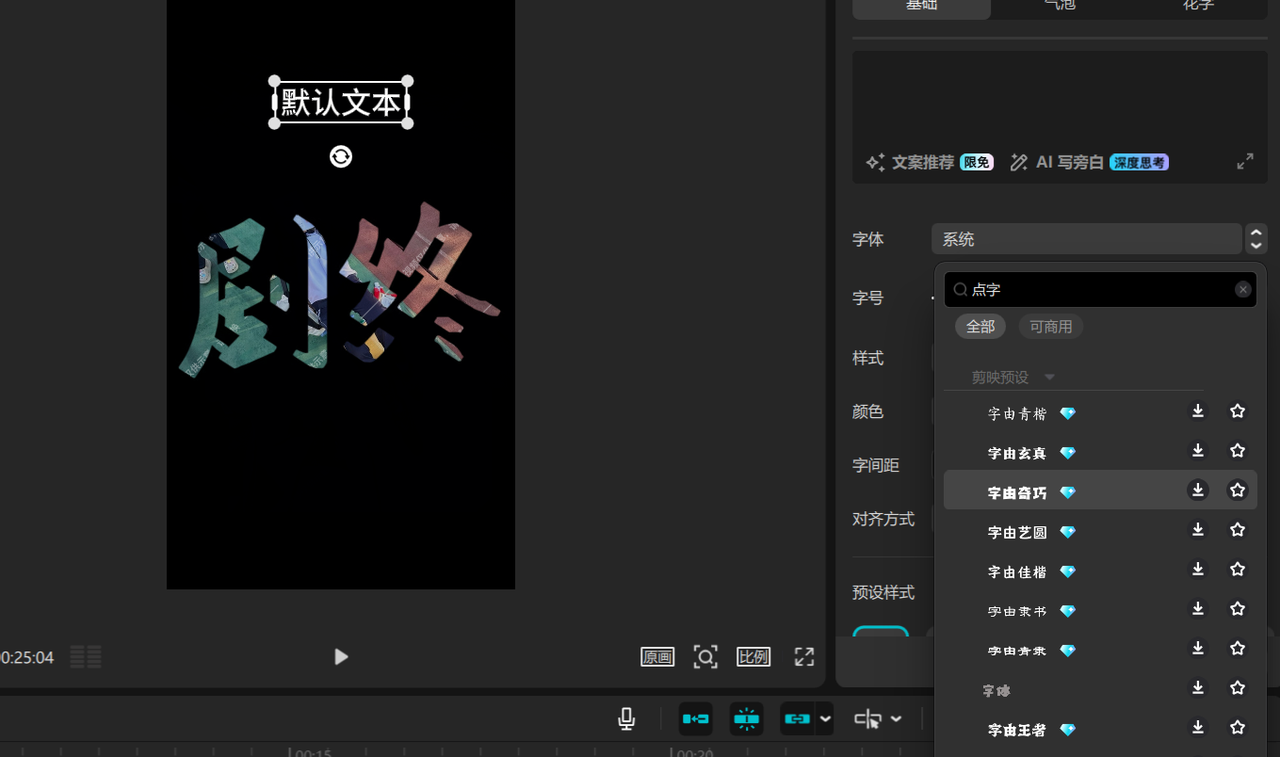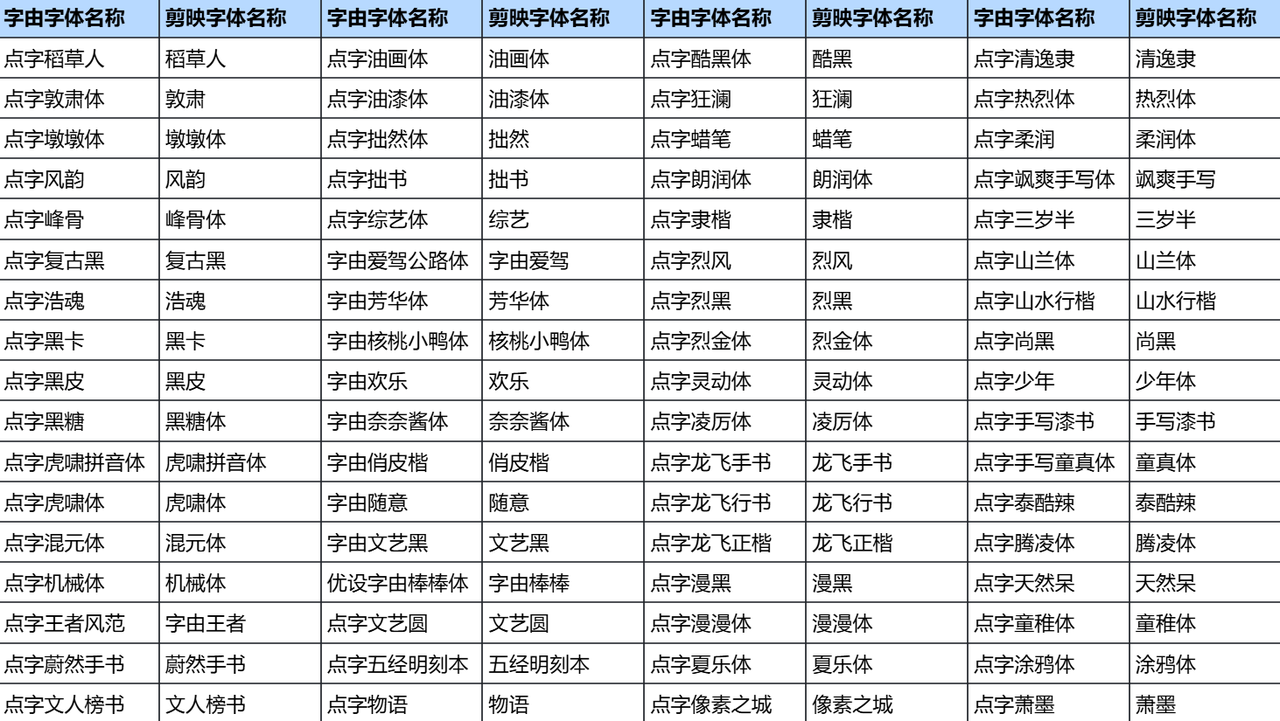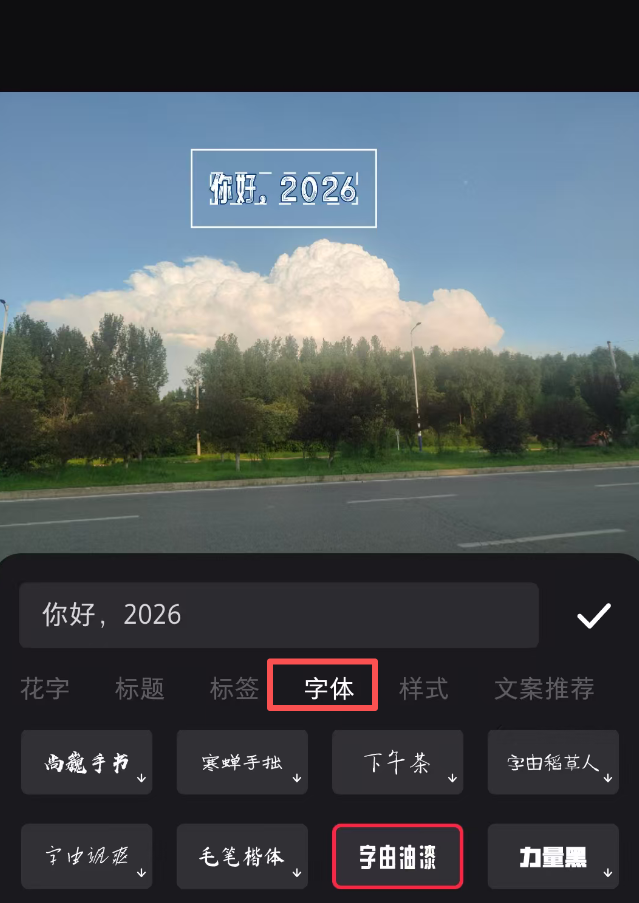
字由字体嵌入合作的案例分享
字由字体嵌入合作介绍
内容创作平台目前普遍在字体上遇到这些问题:既需要丰富多元的字体资源满足创意设计需求,更高度重视素材版权合规性,规避商用侵权风险,这也成为用户评判、选择创作平台的核心标准。针对行业普遍的字体素材匮乏、版权风险高、使用体验割裂三大痛点,字由依托海量正版字库资源,为合作伙伴提供深度嵌入式字体解决方案。将全套合规字体能力无缝集成至合作产品,化作平台原生内置功能,彻底打通字体使用链路,为终端用户打造无缝流畅、安全合规、品类丰富的一站式字体创作体验。
剪映字体嵌入案例
字由一次性提供了超过 128 款字体,包含标题、创意、手写、艺术字等多种风格,满足各类创作场景。
将这些字体内置到剪映软件中,用户在使用剪映制作的视频时,可以直接在软件中切换不同的字体,为视频选择最合适的字体。
128 款字体名称对应信息如下,您可以在字由官网上,提前查看字体样式以及预览字体效果,在剪映后台进行搜索字体名称进行使用。
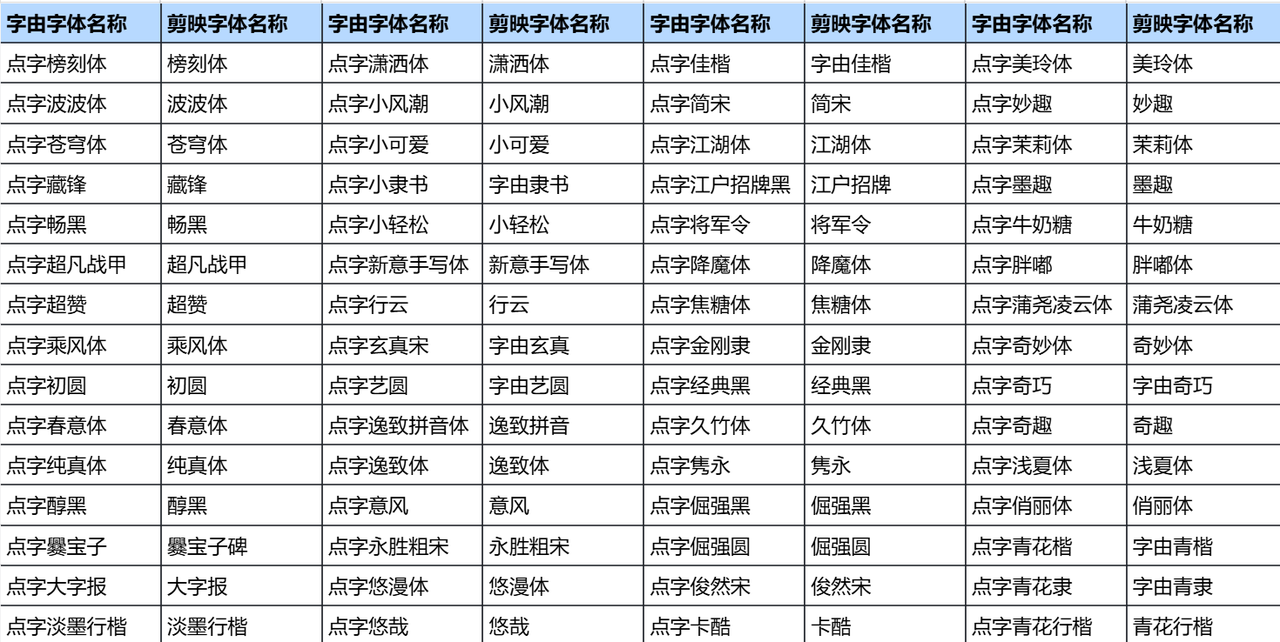
小红书字体嵌入案例
字由精心筛选并提供了多款契合平台“生活美学”、“真实分享”调性的字体入驻小红书。这些字体视觉上更具手写感、松弛感与亲和力,完美适配日常Vlog、好物笔记等内容形式,从视觉设计层面帮助用户和平台提升内容的质感与辨识度。
Canva 字体嵌入案例
字由字体嵌入方式比较简单,将字由丰富的原创字体打包,放到 Canva 的设计后台编辑器中,用户可以在设计的时候,进行字体的切换和使用。
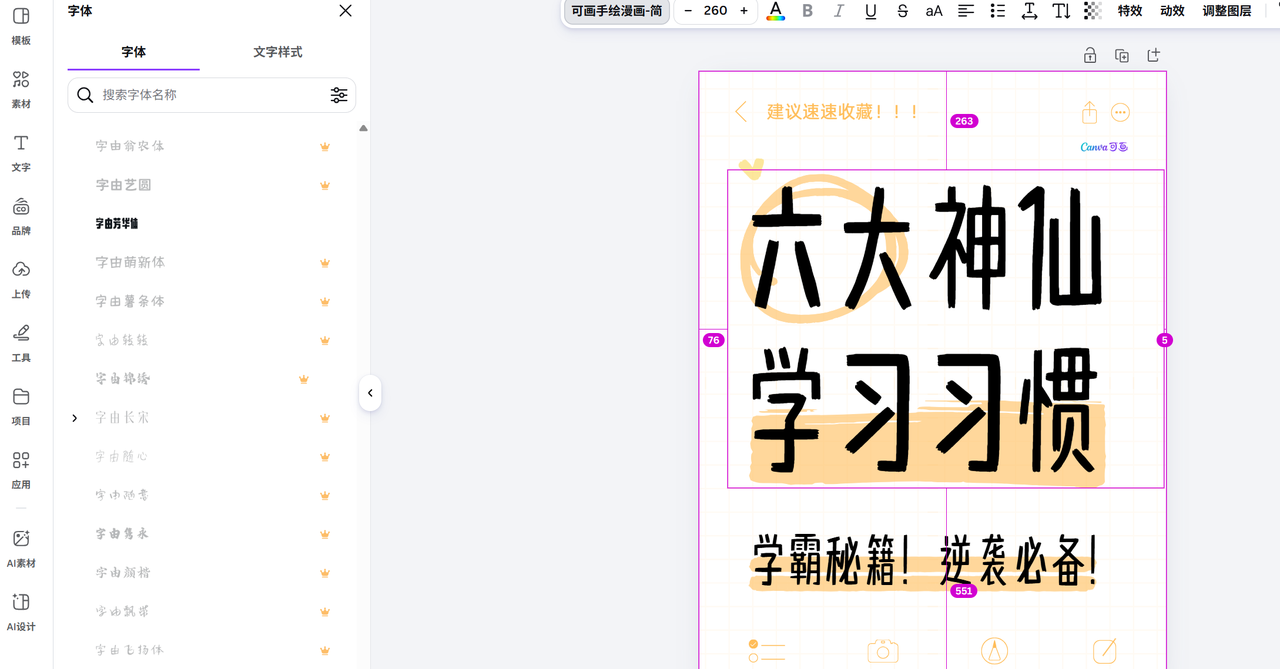
在Canva等在线设计平台,嵌入式字体库让用户在设计海报、社交媒体图片时,能直接调用高质量的正版字体,极大降低了普通用户的创作门槛与版权风险。
字体嵌入的优势
降低创作使用门槛,全面提升产出效率
平台搭载海量内置字体资源,创作者无需跳转外部渠道搜索、下载、安装字体,全部字体调取、切换、预览操作均可在编辑器内一站式完成,省去多软件切换、本地安装调试的繁琐流程,大幅压缩素材准备耗时,显著提升整体创作效率。